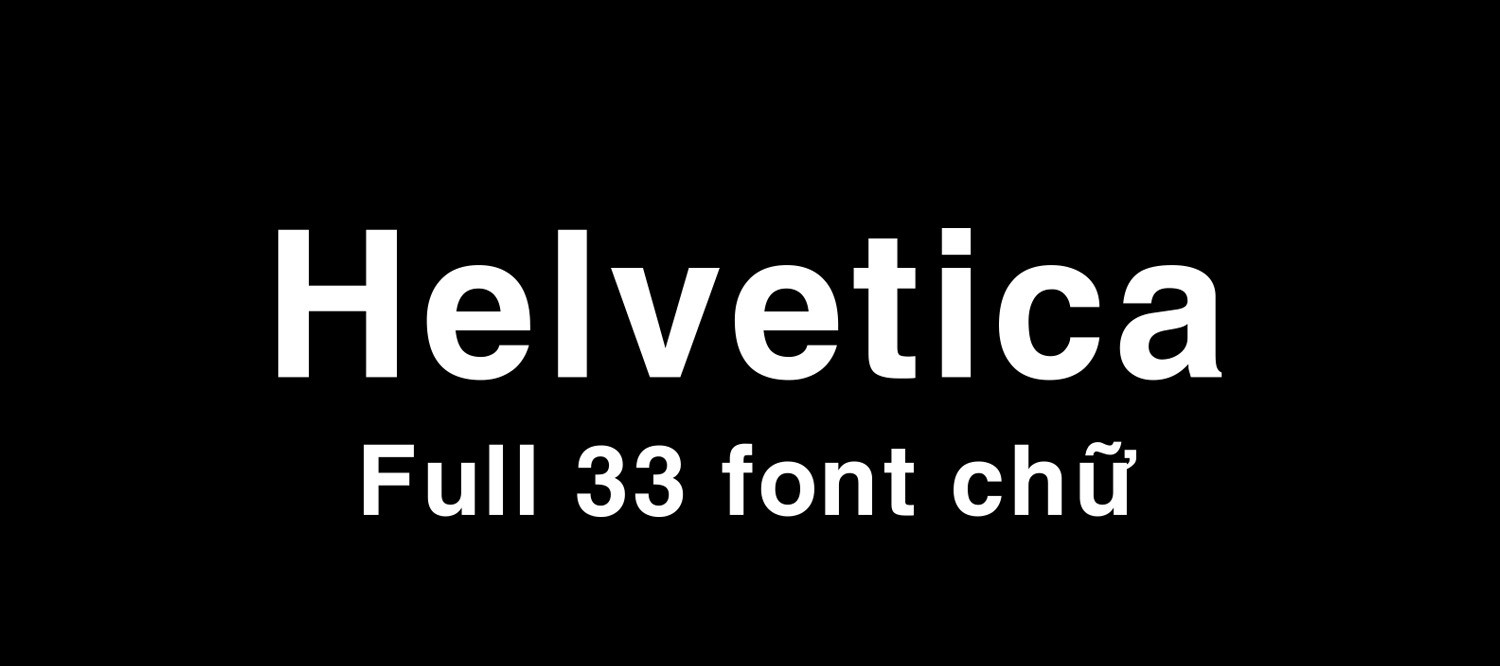
Helvetica là một trong những font chữ sans-serif nổi tiếng nhất thế giới, được thiết kế bởi Max Miedinger và Eduard Hoffmann vào năm 1957. Được xem là biểu tượng của thiết kế hiện đại, Helvetica đã trở thành lựa chọn ưa thích của các nhà thiết kế, thương hiệu và các công ty trên toàn cầu. Font chữ này nổi bật với sự đơn giản, rõ ràng, dễ đọc và không bị ảnh hưởng bởi thời gian, làm cho nó trở thành một phần không thể thiếu trong nhiều dự án thiết kế.
Dễ đọc: Dù ở kích thước lớn hay nhỏ, Helvetica vẫn đảm bảo tính dễ đọc, nhờ vào khoảng cách giữa các chữ cái và độ tương phản giữa nét đậm và nét nhạt.
Tính linh hoạt: Helvetica có thể ứng dụng trong nhiều ngữ cảnh khác nhau, từ thiết kế đồ họa, in ấn đến giao diện người dùng.
Tính trung lập: Helvetica không mang quá nhiều cảm xúc, nó tạo ra một cảm giác trung lập, chuyên nghiệp và đáng tin cậy.
Helvetica được tạo ra vào năm 1957 tại Thụy Sĩ, ban đầu với tên gọi "Neue Haas Grotesk." Đến năm 1960, font chữ này được đổi tên thành "Helvetica" - lấy cảm hứng từ "Helvetia," tên Latin của Thụy Sĩ. Ngay từ khi ra đời, Helvetica đã nhận được sự chú ý lớn từ cộng đồng thiết kế nhờ vào sự đơn giản và tính hiệu quả trong việc truyền tải thông điệp.
Trong những năm 1960 và 1970, Helvetica nhanh chóng trở thành một trong những font chữ được sử dụng rộng rãi nhất trong thiết kế đồ họa và quảng cáo. Nhiều thương hiệu lớn đã chọn Helvetica làm font chữ chính trong bộ nhận diện thương hiệu của mình, nhờ vào tính dễ nhận diện và khả năng phù hợp với nhiều ngữ cảnh khác nhau.
Quá trình Việt hóa Helvetica là việc chuyển đổi font chữ này để hỗ trợ đầy đủ các ký tự tiếng Việt. Điều này bao gồm việc thêm vào các dấu tiếng Việt như dấu sắc, huyền, hỏi, ngã, nặng và các ký tự đặc biệt khác của tiếng Việt. Với việc Việt hóa, Helvetica đã trở thành một công cụ mạnh mẽ cho các nhà thiết kế Việt Nam, cho phép họ sử dụng font chữ này trong các dự án thiết kế mang tính quốc tế cũng như trong các tài liệu văn bản tiếng Việt.
Helvetica, với thiết kế tinh giản và tính dễ đọc vượt trội, đã trở thành một trong những lựa chọn hàng đầu cho các nhà thiết kế thương hiệu trên toàn thế giới. Tính trung lập của Helvetica cho phép nó hòa hợp với nhiều phong cách thiết kế khác nhau, từ cổ điển đến hiện đại, giúp tạo ra một hình ảnh chuyên nghiệp và đáng tin cậy.
Xây dựng nhận diện thương hiệu mạnh mẽ: Nhiều thương hiệu lớn như American Airlines, BMW, và Microsoft đã tin tưởng lựa chọn Helvetica để xây dựng nên một bộ nhận diện thương hiệu thống nhất và dễ nhận biết.
Truyền tải thông điệp rõ ràng: Trong các tài liệu tiếp thị, Helvetica giúp truyền tải thông điệp một cách hiệu quả, thu hút sự chú ý của khách hàng và tạo ấn tượng sâu sắc.
Ứng dụng đa dạng: Từ logo, ấn phẩm, đến các vật phẩm quảng cáo, Helvetica đều thể hiện được sự linh hoạt và phù hợp với nhiều mục đích sử dụng.
Tại sao Helvetica lại phổ biến?
Tính linh hoạt: Như đã nói ở trên, Helvetica có thể sử dụng trong nhiều lĩnh vực khác nhau, từ thiết kế logo, poster đến giao diện website.
Tính dễ đọc: Tính dễ đọc của Helvetica giúp cho thông tin được truyền tải một cách rõ ràng và hiệu quả.
Tính hiện đại: Thiết kế đơn giản, tinh tế của Helvetica phù hợp với xu hướng thiết kế hiện đại, tối giản.
Tính phổ biến: Helvetica đã được sử dụng rộng rãi trong nhiều năm, trở thành một tiêu chuẩn trong ngành thiết kế.
Việc sử dụng Helvetica Việt hóa trong các dự án thiết kế mang lại sự nhất quán cao, đặc biệt khi kết hợp các văn bản tiếng Việt và tiếng Anh trong cùng một tài liệu. Sự thống nhất về font chữ giúp tạo ra một hình ảnh chuyên nghiệp và liền mạch, góp phần tăng cường sự nhận diện thương hiệu và thu hút người xem.
Helvetica Việt hóa giữ nguyên các đặc điểm dễ đọc của font chữ gốc, đảm bảo rằng văn bản tiếng Việt vẫn rõ ràng và dễ tiếp cận. Điều này đặc biệt quan trọng trong các tài liệu dài, nơi mà tính dễ đọc là yếu tố then chốt để giữ chân người đọc.
Sử dụng Helvetica trong các thiết kế tiếng Việt mang lại một phong cách hiện đại và chuyên nghiệp, phù hợp với nhiều loại dự án khác nhau từ quảng cáo, truyền thông, đến thiết kế thương hiệu. Helvetica giúp tạo nên một hình ảnh đáng tin cậy và hấp dẫn, phù hợp với những thương hiệu muốn xây dựng một vị thế mạnh mẽ trên thị trường.
Khi sử dụng Helvetica Việt hóa, việc lựa chọn màu sắc phù hợp là điều quan trọng để đảm bảo rằng văn bản của bạn nổi bật và dễ đọc. Hãy chọn những màu sắc có độ tương phản cao giữa nền và văn bản để tăng cường tính rõ ràng và thu hút sự chú ý.
Helvetica hoạt động tốt với nhiều kích thước khác nhau, nhưng việc sử dụng kích thước và khoảng cách giữa các ký tự một cách hợp lý sẽ giúp văn bản của bạn trở nên dễ đọc hơn. Hãy điều chỉnh khoảng cách giữa các dòng và chữ cái để đảm bảo tính thẩm mỹ và hiệu quả của văn bản.
Helvetica Việt hóa có thể kết hợp tốt với nhiều font chữ khác để tạo nên sự đa dạng và phong phú cho thiết kế của bạn. Hãy thử nghiệm kết hợp Helvetica với các font chữ serif hoặc script để tạo ra những thiết kế độc đáo và ấn tượng.
Sử dụng Helvetica Việt hóa trong các dự án thiết kế không chỉ giúp bạn duy trì sự nhất quán và chuyên nghiệp, mà còn giúp nâng tầm giá trị thương hiệu của bạn. Bằng cách hiểu rõ và áp dụng đúng các nguyên tắc sử dụng font chữ này, bạn có thể tạo ra những sản phẩm thiết kế chất lượng cao, thu hút sự chú ý của người xem và ghi dấu ấn mạnh mẽ trong lòng khách hàng.